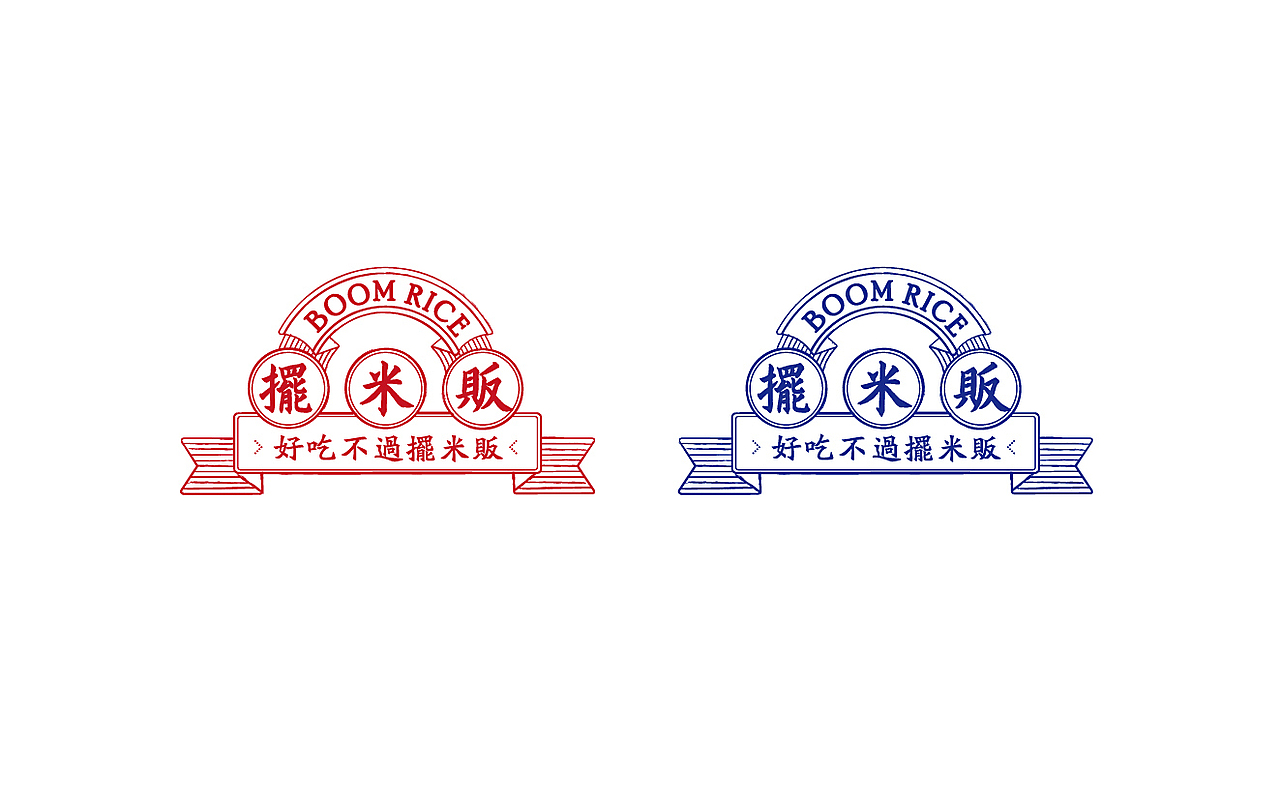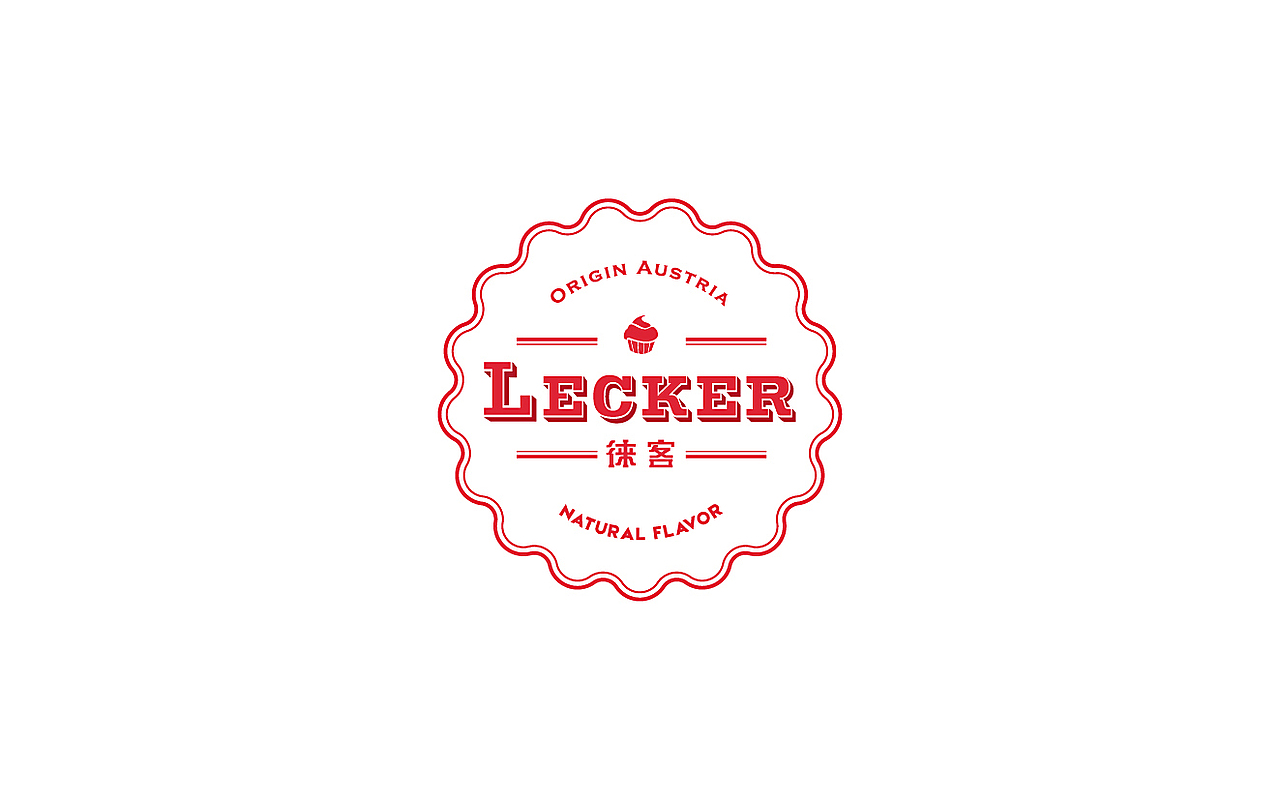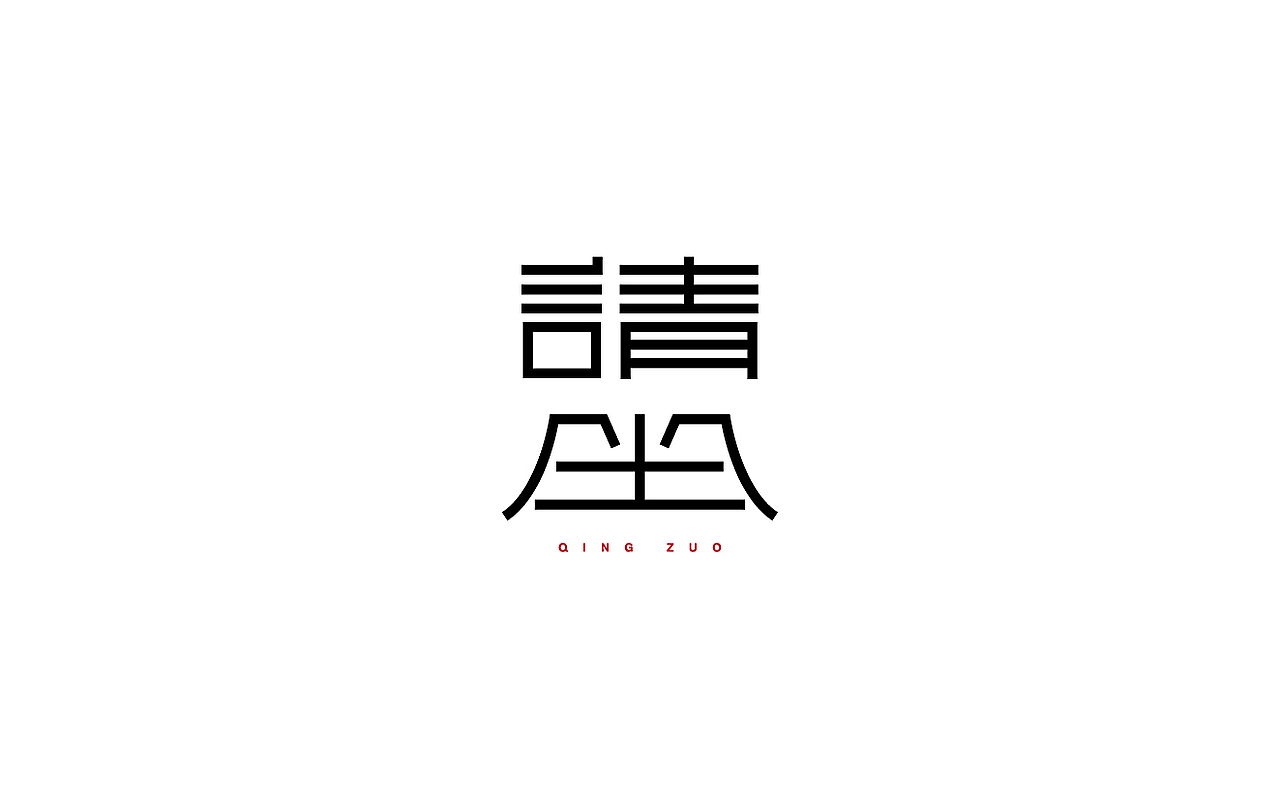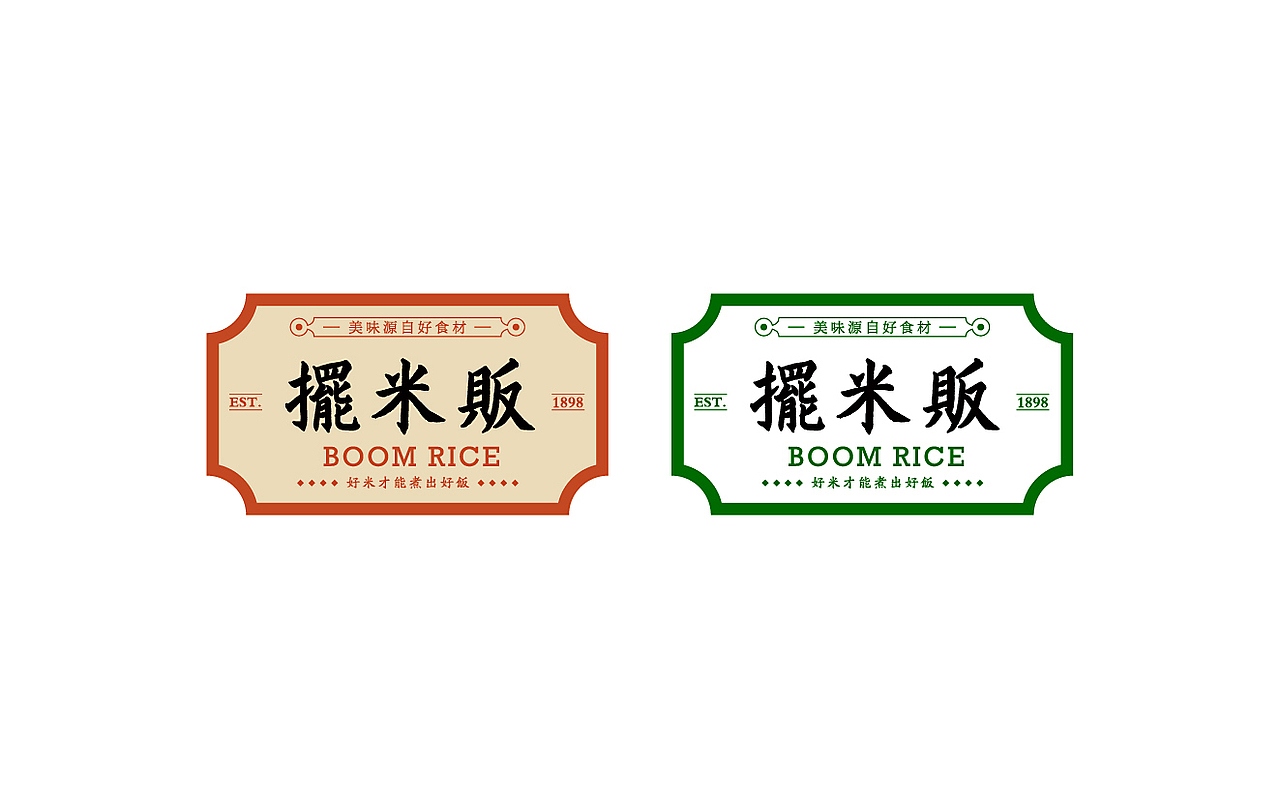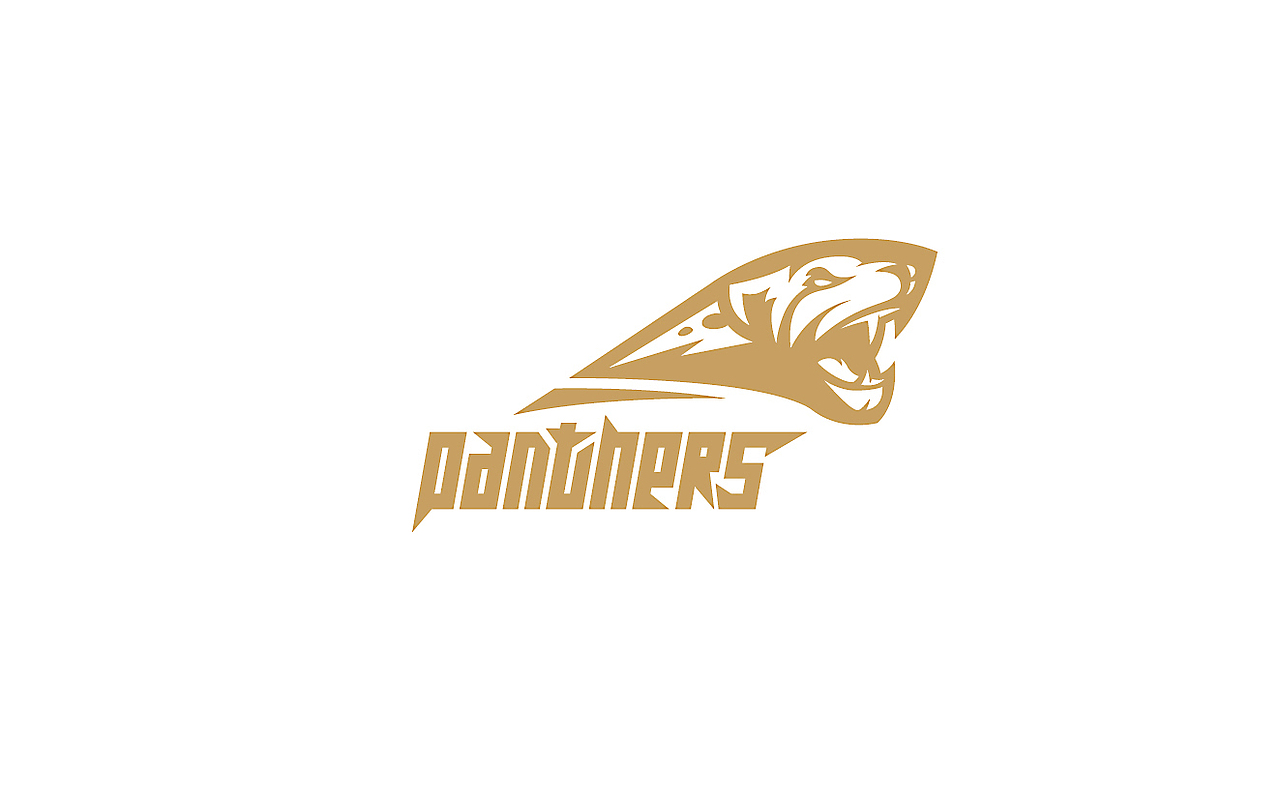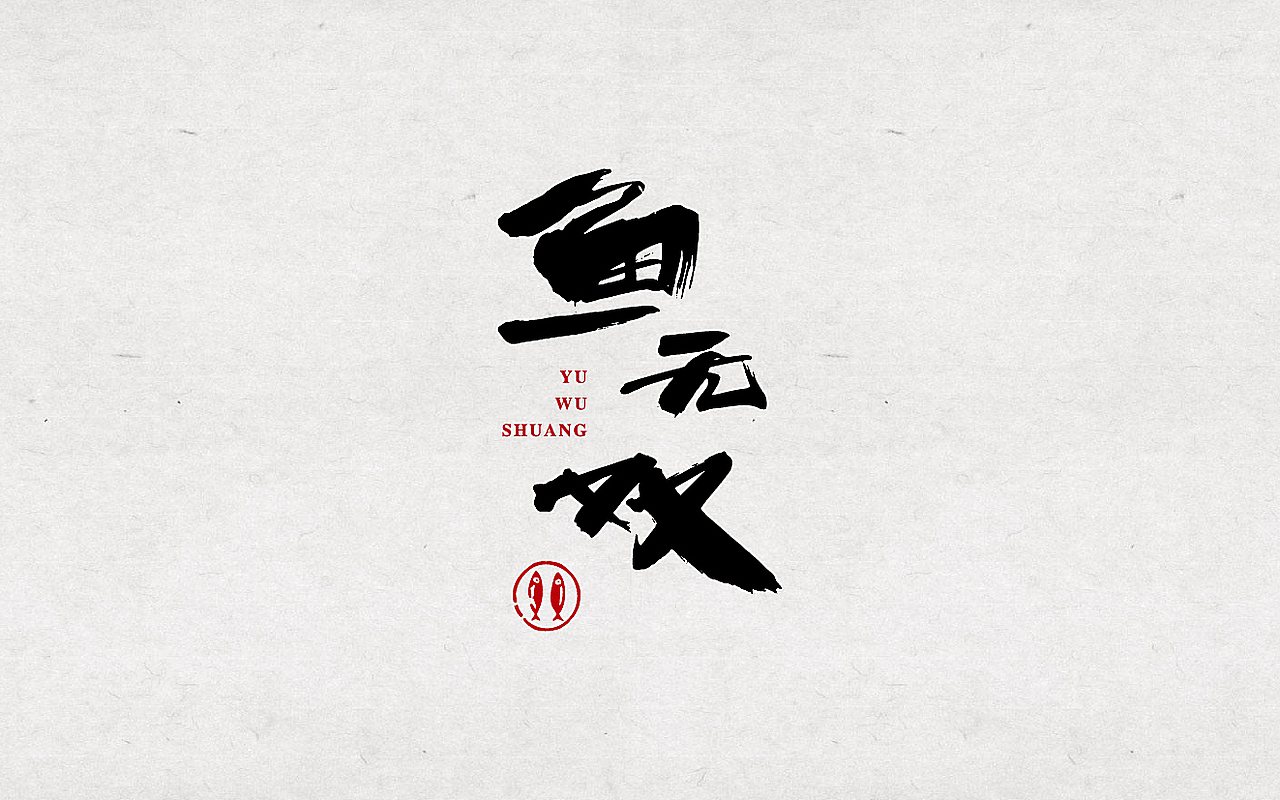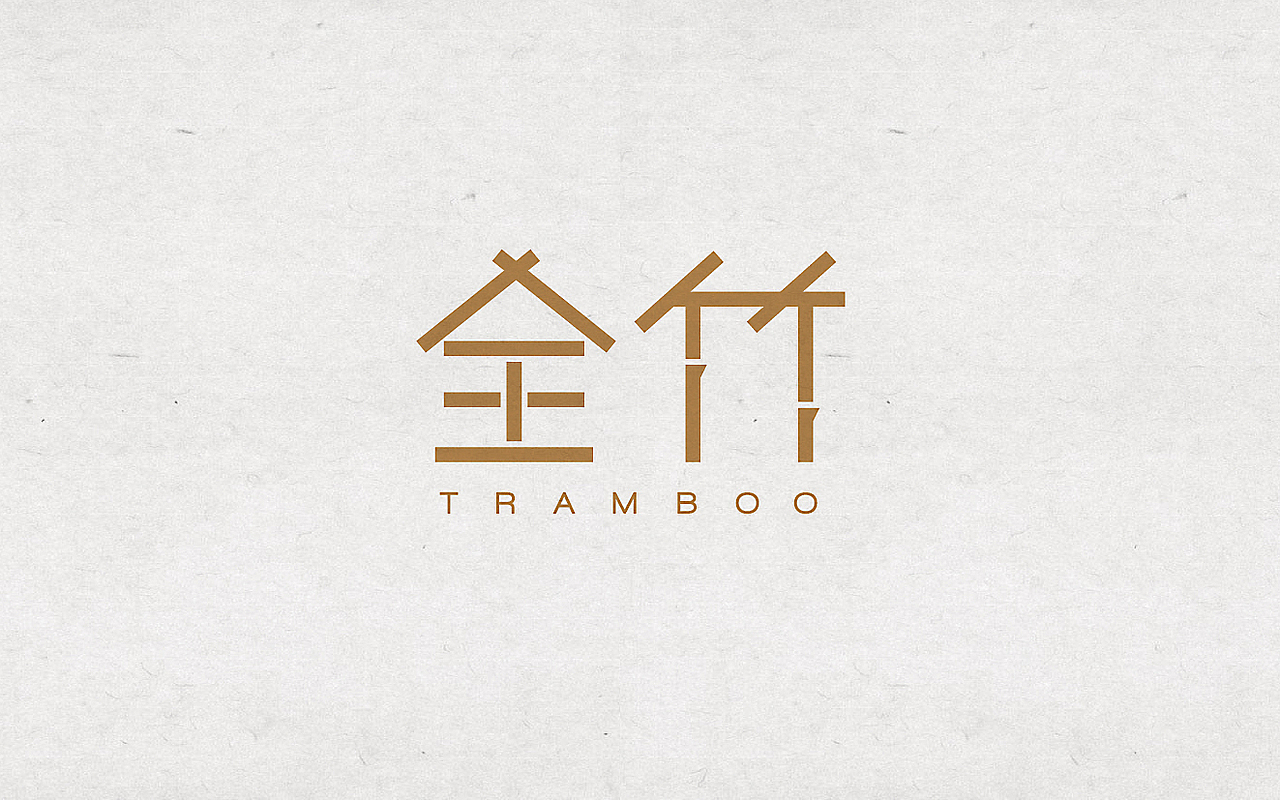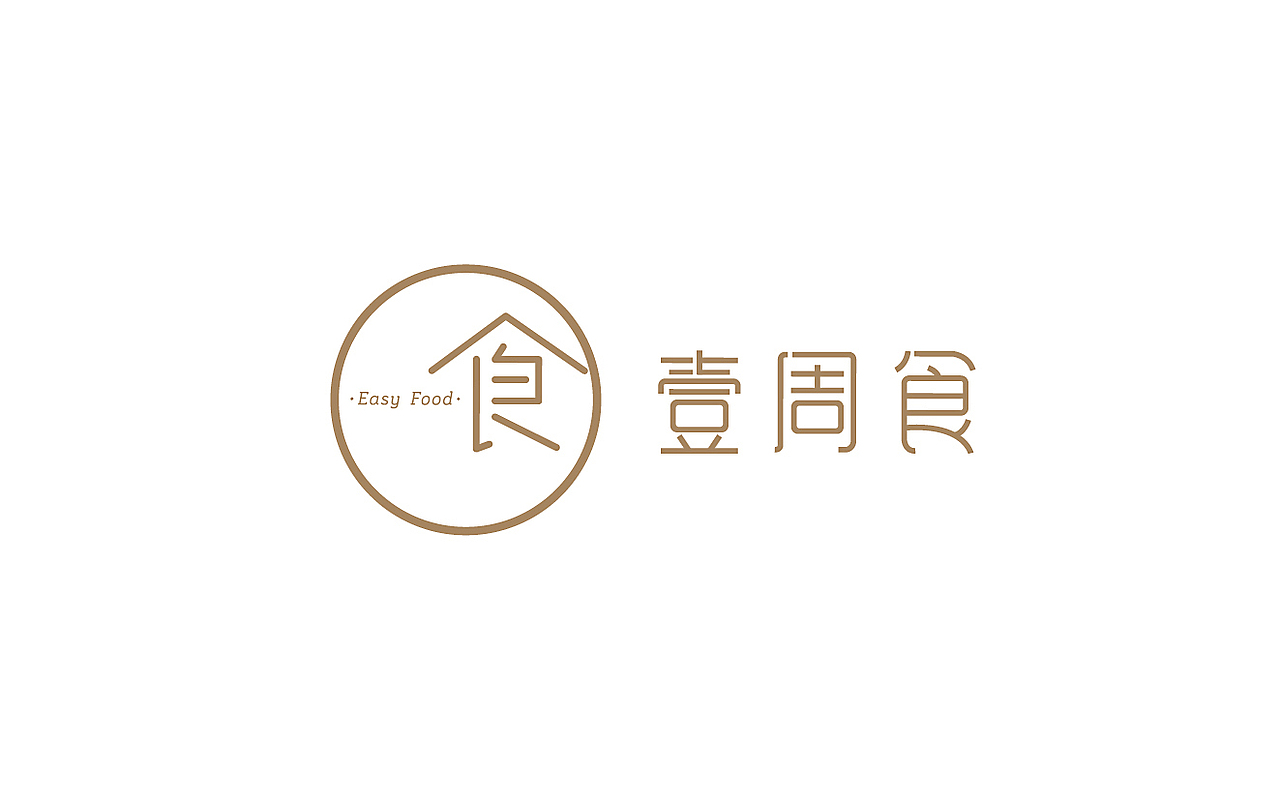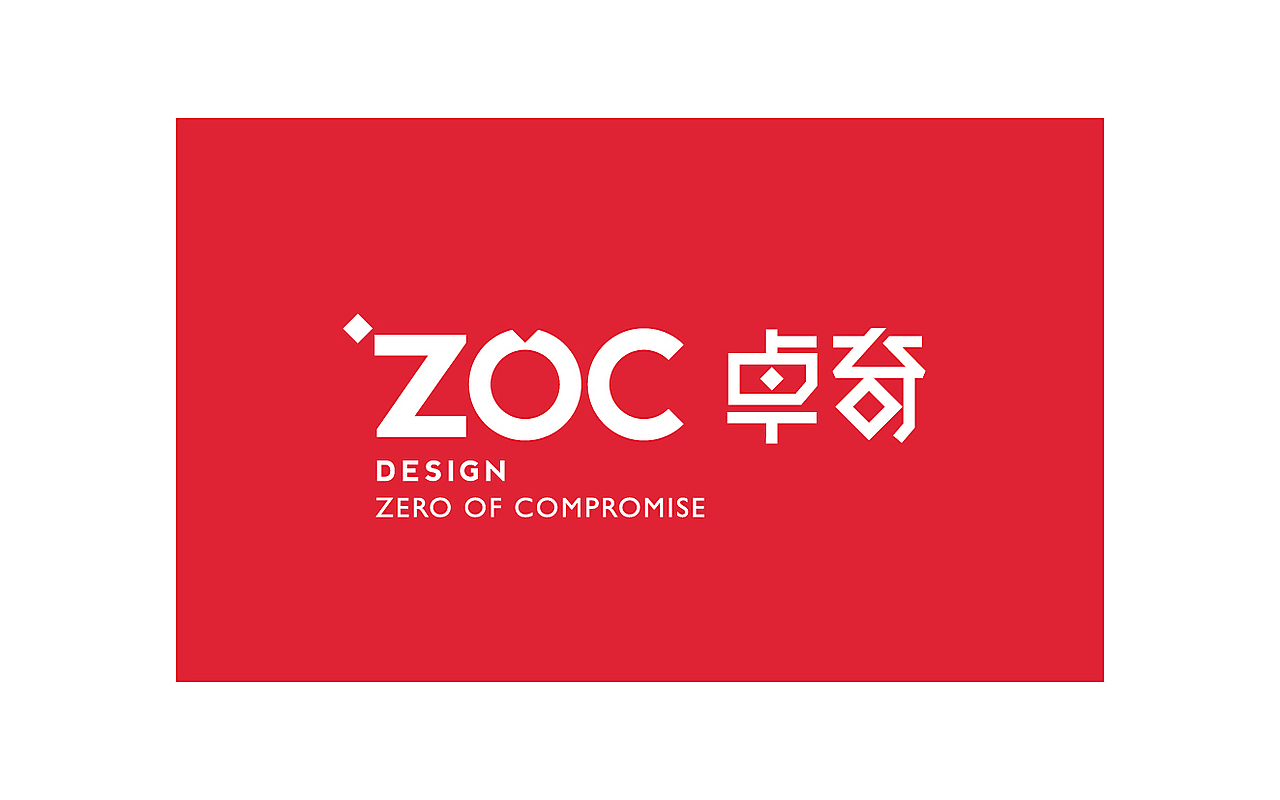
力昂品牌|2016上半年部分LOGO/字体 设计集锦
下面是部分二零一六年的LOGO与字体设计,
挑了一些说的过去的,与大家交流交流,
我依然坚持我的观点就是,
在没有成为大师之前,就不要谈什么个人风格了,
品牌不一样,品类不一样,细分不一样,风格也一定不一样~
一定要设计出合适的~
[收故事的老万] 个人品牌
健康膳食外卖品牌
鲜榨果汁/便当 零售店品牌
奥地利进口甜品品牌
主打坚果的轻食品牌
飞机稿了
鲜榨果汁/便当 零售店品牌
北京的客户,越南菜餐厅,在各大shopping mall 开了N家店了,只是品牌都不一样
飞机稿了
南京鱼锅品牌—椒麻鱼好吃,生意爆好
茶品牌
茶品类字体设计
中西简餐 餐饮品牌
飞机稿
出口刀具品牌飞机稿
飞机稿
竹制品品牌
飞机稿
电视机品牌
飞机稿
商贸公司品牌
南京二十年老店-龙宫龙虾在南京非常出名,口味太赞
飞机稿了,南京一家比较资深的UI设计公司
飞机稿
汽车美容
以玉米为主的食品品牌
北京的客户,越南菜餐厅,在各大shopping mall 开了N家店了,只是品牌都不一样
飞机稿